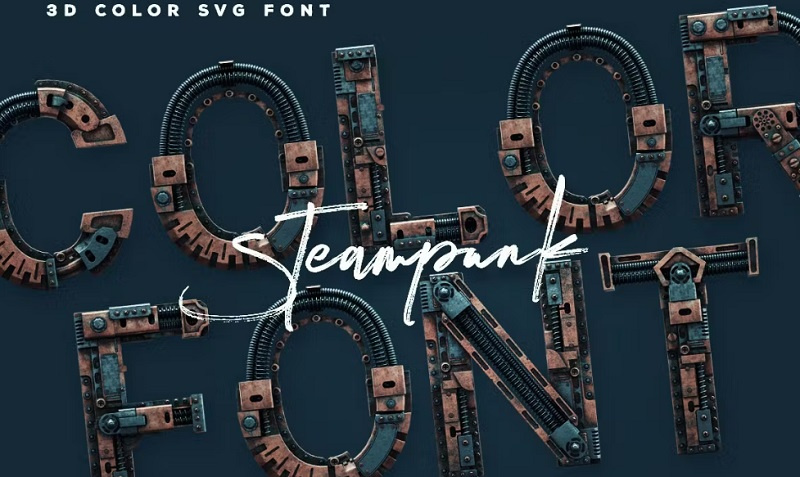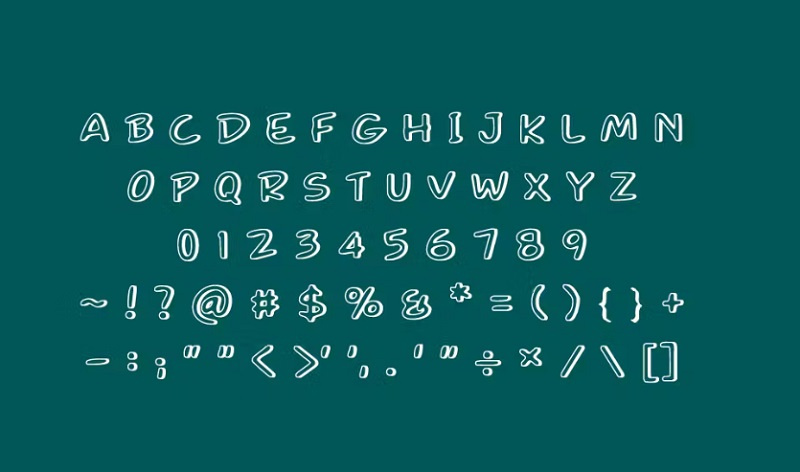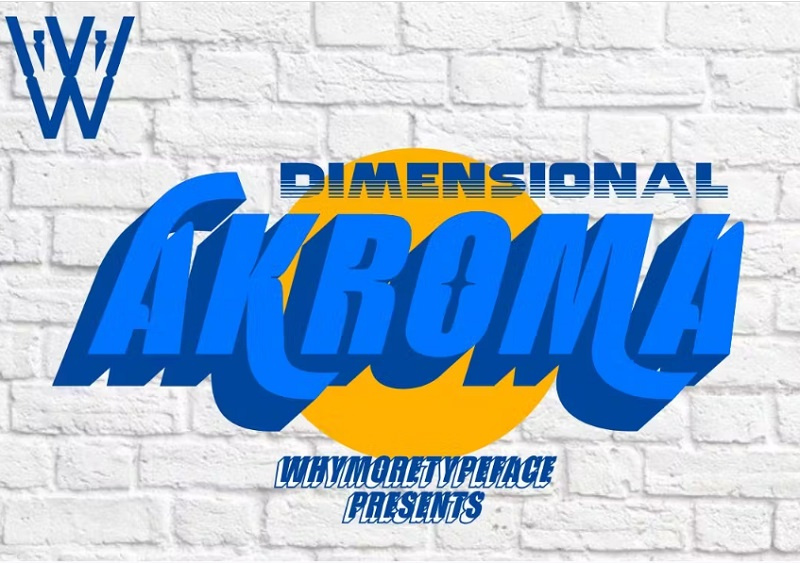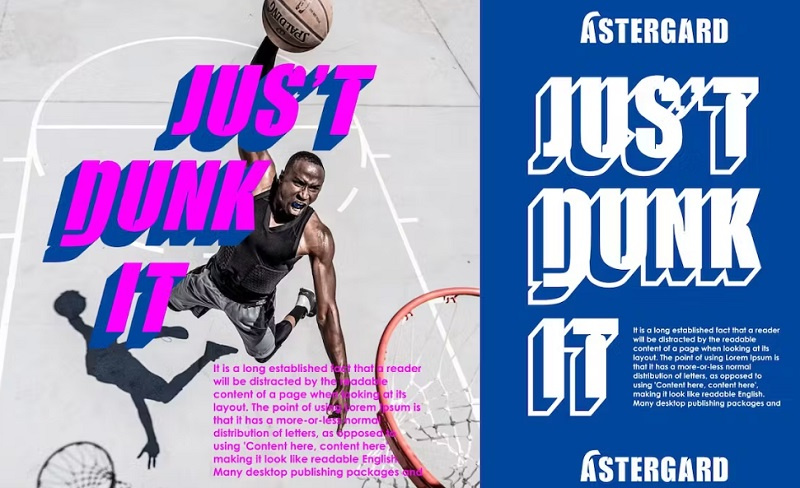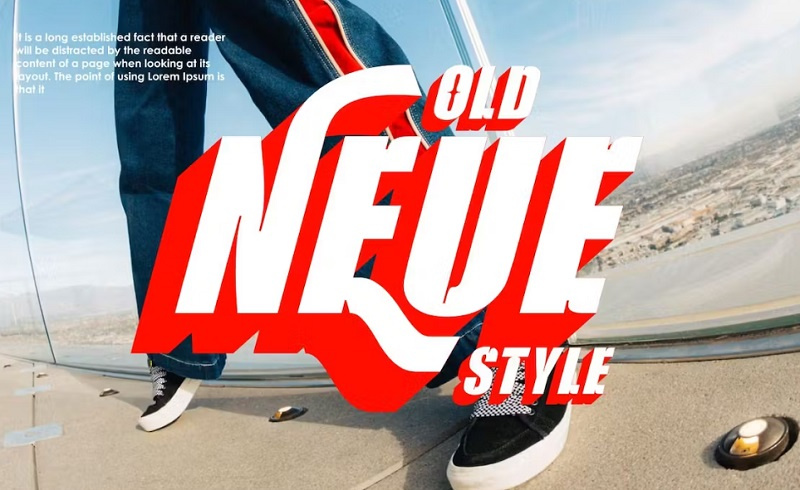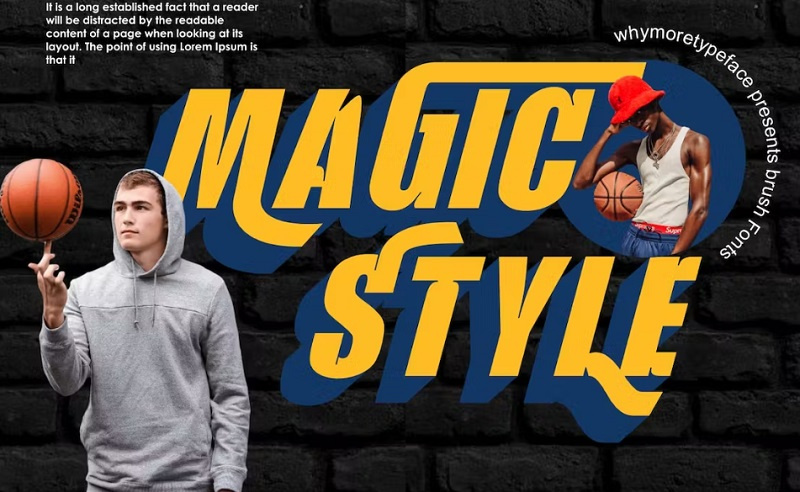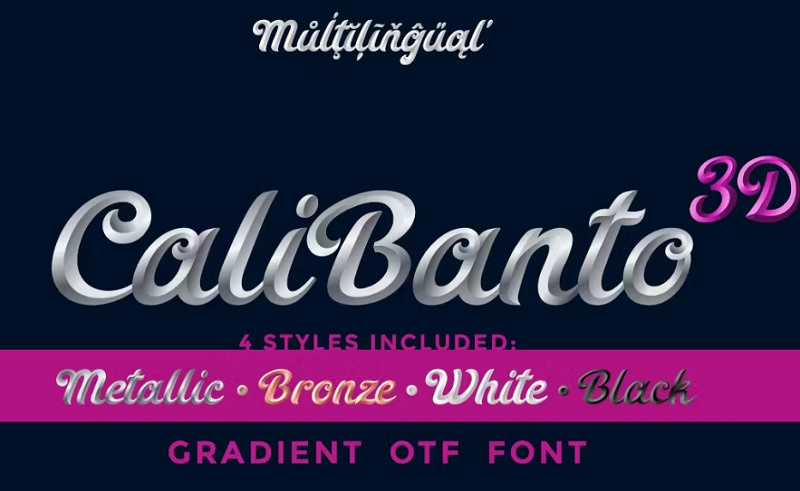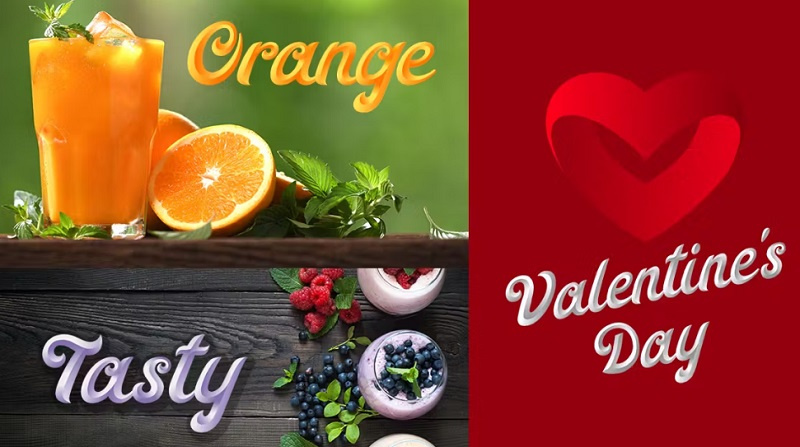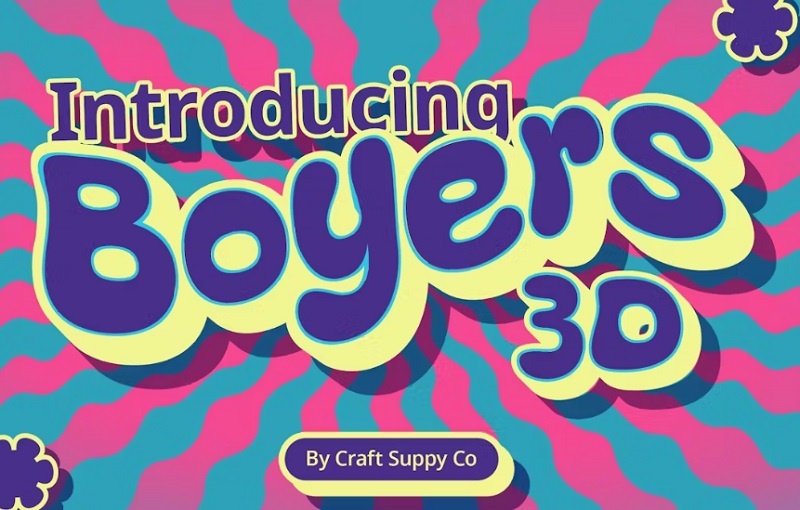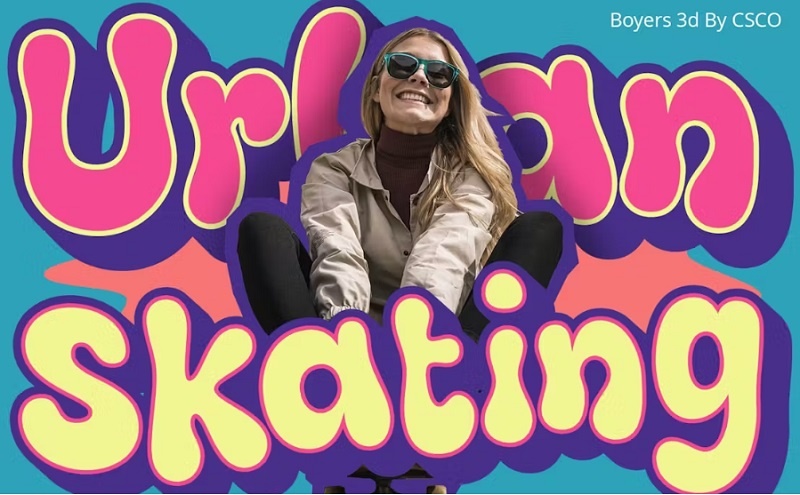
فونت انگلیسی سه بعدی
فونت انگلیسی سه بعدی شامل 6 فونت انگلیسی 3بعدی از سایت gfx می باشد. یکی از بهترین گزینه ها برای طراحی های مدرن است. با دانلود فونت انگلیسی سه بعدی می توانید از آن برای جلد کتاب، جلد موسیقی، کتاب کودک، پوستر، تبلیغات، محتوای رسانه های اجتماعی، لوگو و موارد دیگر استفاده کنید.
1- دانلود فونت انگلیسی سه بعدی Akroma
این فونت سه بعدی انگلیسی با سبک نئون، قدیمی و نیمه مدرن ایجاد شده است. همچنین ضخامت فونت می تواند نشان دهنده این باشد که این فونت برای نمایش محصولات ورزشی و اسپرت بسیار مفید است. برای ]دانلود فونت انگلیسی سه بعدی Akroma از جی اف ایکس دانلود در ادامه با ما همراه باشید.
2- فونت سه بعدی انگلیسی CaliBanto 3D
این فونت سه بعدی انگلیسی با نام CaliBanto 3D یک فونت سه بعدی با خط خوشنویسی است که در 4 سبک ارائه شده است از جمله: فلزی، برنز (کمتر براق از فلز)، سفید و سیاه. مناسب برای انواع طراحی های گرافیکی می باشد.
3- مجموعه فونت های سه بعدی انگلیسی
در این مطلب با معرفی یکی دیگر از مجموعه فونت های سه بعدی انگلیسی با نام Boyers 3D با شما عزیزان همراه هستیم. این فونت سه بعدی حس بازیگوشی، فانتزی، شادی و زیبایی را به طرح های شما اضافه می کند.
4- فونت سه بعدی انگلیسی برای اینشات
فونت‌های سه بعدی انگلیسی، یکی از جذاب‌ترین و مدرن‌ترین روش‌ها برای افزودن متن به ویدیوهای اینشات هستند. این فونت‌ها با ایجاد عمق و برجستگی، به ویدیوهای شما جلوه‌ای حرفه‌ای و سینمایی می‌دهند. مناسب برای برای ایجاد تیزرهای تبلیغاتی جذاب، نمایش عناوین و توضیحات در کلیپ‌های آموزشی یا معرفی محصول می باشد. این فونت سه بعدی انگلیسی برای اینشات با فایل های .otf & .ttf ارائه شده است.